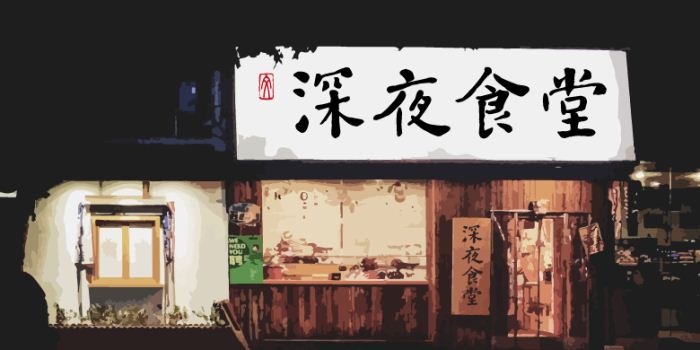
書體坊何紹基楷由方正字庫禚效鋒設(shè)計師出品的藝術(shù)字體,該字字形含蓄內(nèi)斂,有靜穆氣息,在運筆上,中正平和,起筆多呈裹鋒,有綿里裹鐵的力量感,適合應(yīng)用于藝術(shù)設(shè)計、平面宣傳設(shè)計、網(wǎng)頁設(shè)計,書法等領(lǐng)域。
何紹基是清代晚期的著名書法家,其楷書由顏體入門,字形含蓄內(nèi)斂,有靜穆氣息,在運筆上,中正平和,起筆多呈裹鋒,有綿里裹鐵的力量感,撇畫行筆輕盈,捺筆頓鋒收筆較重,勾畫多細(xì)絲;整體書風(fēng)有顏體的氣魄,亦有歐體的險絕。本字體,由書體坊禚效鋒集何紹基楷書代表作制作而成,是一款優(yōu)秀的書法字體。。。